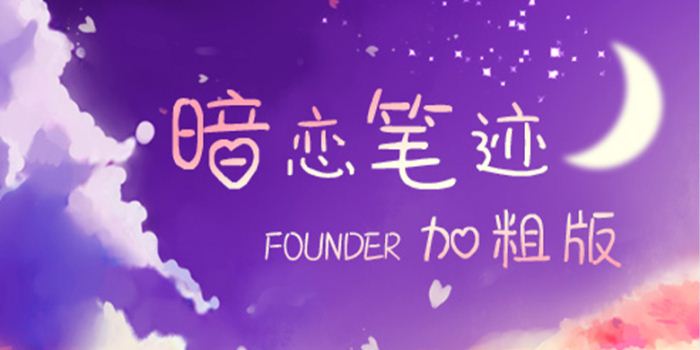
方正手跡-暗戀筆跡加粗版由方正字庫王航設計師出品的藝術字體,該字圓潤的轉角處理,溫婉迷人,加上化“口”為愛心,簡直是少女氣息滿滿,適合應用于藝術設計、平面宣傳設計、網(wǎng)頁設計,書法等領域。
寬松的中宮,簡潔的筆畫,輕松大方的字形,圓潤的轉角處理,溫婉迷人,加上化“口”為愛心,簡直是少女氣息滿滿,閱讀起來有心動的感覺。適用于少年兒童類的書刊、品牌廣告和產(chǎn)品包裝設計,以及社交網(wǎng)絡的個性化用字。。